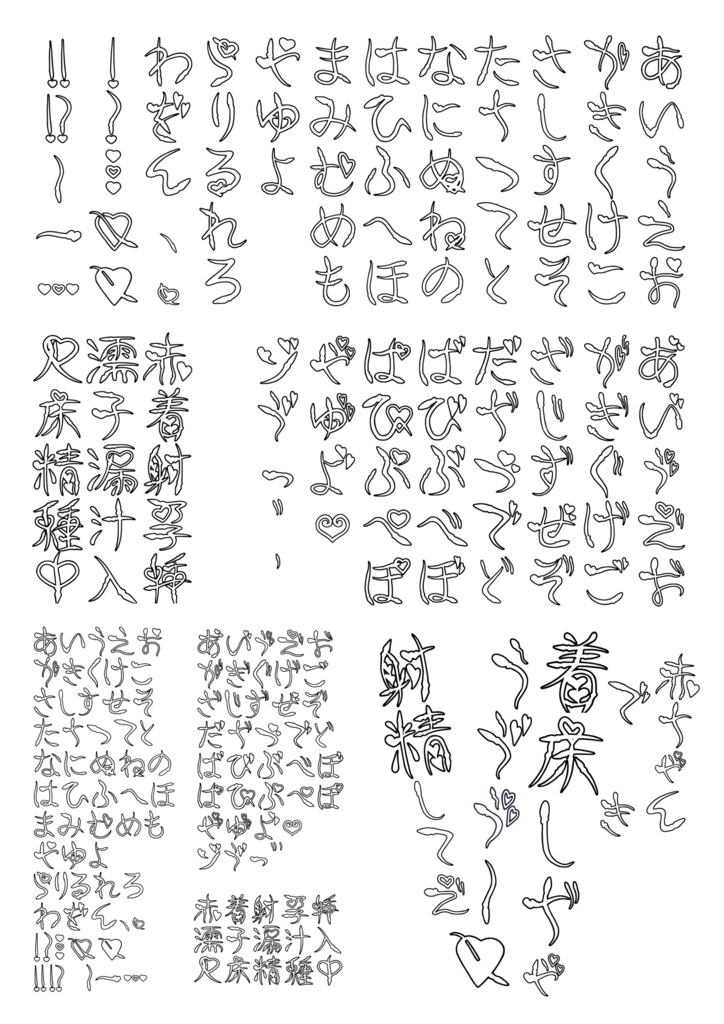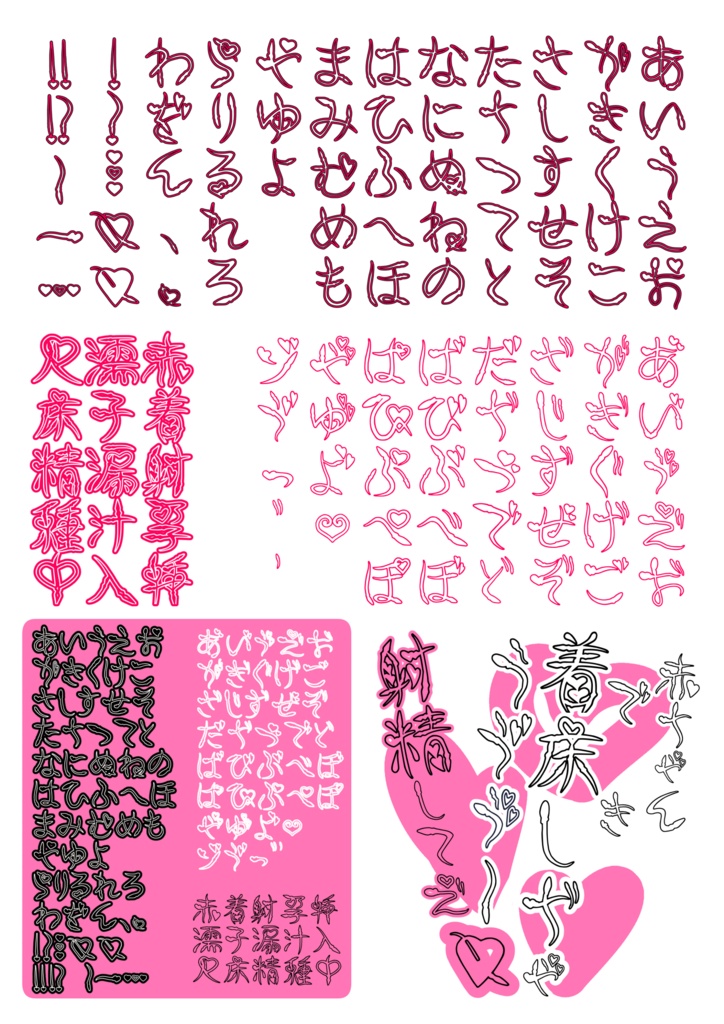
おたまフォント
「読めないわけじゃないけれども汚い」 と友人に笑われる自分の文字を活かした えっちな場面に使えるフォント第三弾です。 今回のフォントは赤ちゃんができちゃいそうな幸せなシーン などにぴったりなデザインで、オノマトペやセリフに ちょうど良いと思うのでよろしければみなさまもどうぞ。 また今回は通常のひらがな・記号に加え、新しい試みとして アルファベットの位置に "そういうシーンでよく使いそうな漢字" を厳選して15文字分追加してあります。 フォント内容 ・通常ひらがなの五十音 ・記号 ・エロシーンに適した漢字15文字 otfとttfが用意されていますのでお使いのソフトに合わせて 適応し易い方をお使いください。 データの中には利用規約等が記載されていますので、 同梱の「read_me.txt」をよくご覧になってからご利用ください。 また、もう一つテキストファイルが内包されていますが そちらは漢字を使う際の注意点や、 アルファベットの振り分け一覧となっていますので 合わせてご確認をお願いします。 こちらのフォントは今後、 さらにカタカナや漢字の数を増やしたものも出す予定です。 その際にはまたお知らせをこちらでさせていただきます。 ファイルの売り方的には汚喘ぎフォントのような形式でやろうと思っています。 とりあえずは冬コミに間に合う形で今回最低限を形にできましたので、 もし今からでも間に合う方は着床確定演出の場面などに ぜひご活用ください。 ------以下、利用規約の一部抜粋です------ ・クレジット表記や事前連絡、利用報告は必要ありません。 ・商用、個人用に関わらず印刷物・映像作品等へ使用が可能です。 ・全フォントデータの著作権は、製作者のぱょったに帰属します。 【OK】 -Webサイトの画像への文字入れ -動画・映像の文字入れ -PDF、ソフトウェアへの埋め込み、ゲームへの使用 【NG】 -フォントファイルの再配布 -自作発言 -商標登録 ----------------------------------------------- 法人様からのお問い合わせをいただくことが増えてきたため、 簡単ではありますが、利用条件を追加明記させていただきます。 ※※※※※※※※※※※※※※※※ 法人利用をご検討中の方へ ※※※※※※※※※※※※※※※※ 本フォントは、同人・個人利用を主として制作しておりますが、 法人様でのご利用も可能です。 法人利用の場合は、実際にフォントをインストールして 使用するパソコン(端末)1台につき1点のご購入をお願いいたします。 (使用人数ではなく、使用端末数を基準としてください) 購入された数を超える端末へのインストール、 ならびに第三者への再配布はご遠慮ください。 制作物への使用(商業作品・業務利用を含む)は、 通常のフォント利用の範囲内で問題ございません。 法人様向けの特別プランや包括ライセンスは、現時点ではご用意しておりません。 ご不明点がございましたら、BOOTHのDMよりお気軽にお問い合わせください。